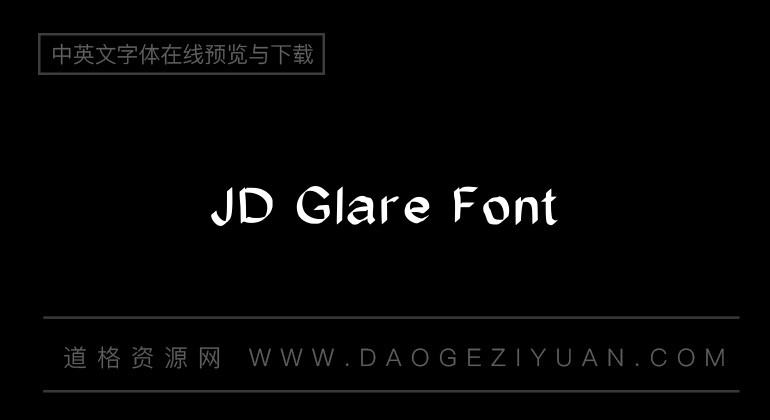
JD Glare Font
JD Glare Font 是一款比较独特富有个性的字体,由于其具有醒目的外观和良好的可读性受到了广泛的欢迎。 这款字体的设计灵感来自于钢筋混凝土建筑物表面上的裂缝和瑕疵,因此具有一种粗糙、独特的视觉效果。该字体的笔画宽度较大,字形较为扭曲,给人一种不规则的感觉,比较适用于突出文本内容的场合。 JD Glare Font 支持多种字符集,包括中文、英文、数字和标点符号,适用于各种场合的设计需求,比如广告宣传、海报设计、标志标识等。
JD Glare Font是一款非常不错的手写艺术字体,具有很好的视觉感,适合于文化类的宣传设计、商业类品牌的广告和产品包装设计以及个性化文字排版等较多场景。